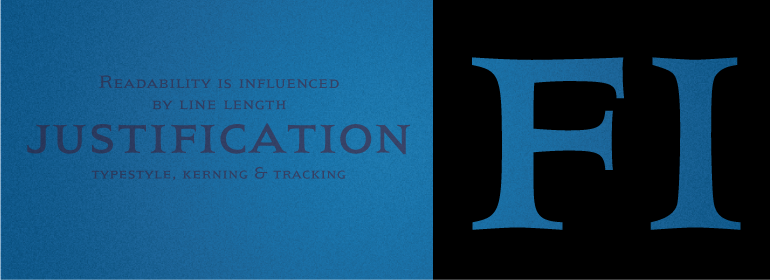
President™
President™,这款字体结构工整、笔画清晰,兼顾美观与易读性,适用于标题、正文、海报、包装、LOGO 等多种场景。字形优雅稳定,风格百搭耐看,适配日常排版与创意设计,让文字呈现更舒适、更具质感。President™一笔一画,皆是细节,以均衡的比例、流畅的线条打造舒适视觉体验,字形端正大气,风格简约现代。无论是商业设计、品牌宣传还是日常排版,都能轻松驾驭,让文字更有格调与力量。President™字体下载。
字体品牌: Linotype(Monotype) 设计师:Frutiger,Adrian 字体分类:衬线体 字体属性:外文 字符集:Unicode 发布时间: 2018
1952年,Charles Peignot做出了一个大胆的举动:他邀请了一位年轻的瑞士设计师到巴黎担任Deberny & Peignot字体铸造厂的艺术总监。这开启了Adrian Frutiger的专业字体设计生涯;从那以后,他设计各种惊人的大师级字体。最早出现在Deberny&Peignot的字体之一是Président,一个具有锋利衬线的拉丁字型。“拉丁文”是对带有楔形或三角形衬线的罗马字体的一种印刷设计,后来Frutiger用他漂亮的Méridien字体又恢复了这种风格。Président™具有宽而坚实的形状;粗细笔画之间的反差很小;还有一种自信的神态。请在名片、公告或艺术标识中使用这种标题字体。”
In 1952, Charles Peignot made a bold and fortuitous move: he invited a young Swiss designer to Paris to be the art director of the Deberny & Peignot type foundry. This started the professional type design career of Adrian Frutiger; and since then he has designed an astonishing range of masterful typefaces. One of the earliest for Deberny & Peignot was Président, a sharp-seriffed Latin titling face. Latin" is a typographic designation for roman typefaces with wedge or triangular-shaped serifs, a stylistic form that Frutiger would return to later with his beautiful typeface Méridien. Président™ has wide, solid shapes; very little contrast between thick and thin strokes; and an air of assurance. Use this titling font for business cards, announcements, or artistic signage."